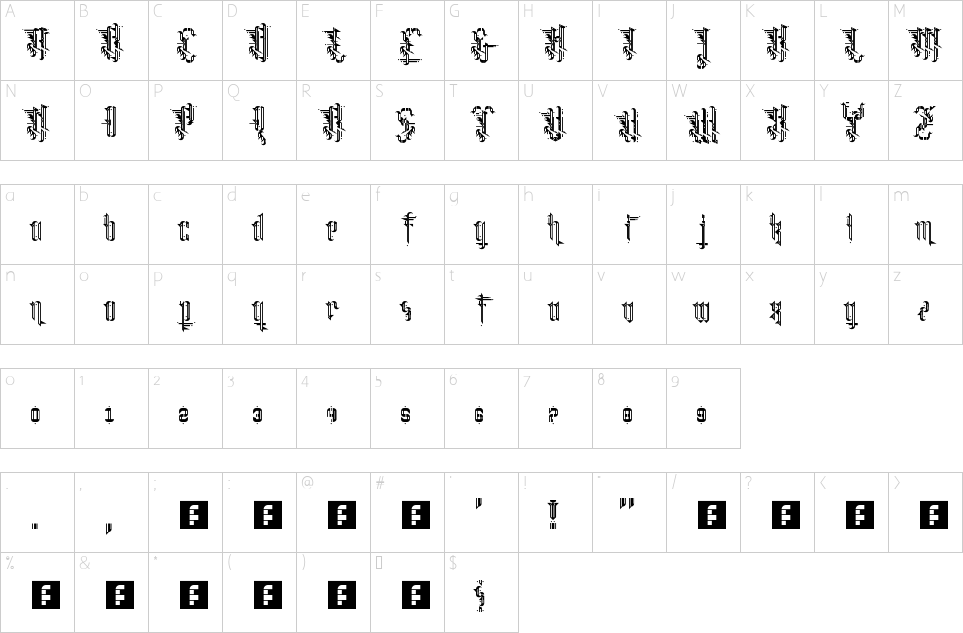
Aqui está uma descrição em português para a página de download da fonte ‘Grimeplex Font – 1001 Free Fonts’, mantendo a essência do texto original e as regras fornecidas: Descubra o poder da Grimeplex, uma fonte gratuita que oferece uma abordagem única para tornar seus projetos ainda mais distintivos. Desenvolvida por Chequered Ink, esta font se destaca não apenas pela sua versatilidade e legibilidade, mas também pelo design moderno e elegante. Grimeplex é a escolha perfeita para designers que desejam incorporar uma personalidade única em seus projetos digitais. Com uma ampla gama de opções estilísticas, Grimeplex permite transformar textos simples em obras de arte vibrantes e únicas. Com sua interface limpa e intuitiva, a Grimeplex está disponível tanto para sistemas operacionais Windows quanto Mac, tornando-a acessível para todos os usuários. Se você busca uma fonte que possa expressar seus ideais criativos com estilo e modernidade, não hesite em experimentar a Grimeplex. Seu design original foi desenvolvido por Chequered Ink, o designer responsável pela criação de uma série de fontes inovadoras e acessíveis. Com sua facilidade de uso e qualidade de impressão avançada, esta font é um verdadeiro trunfo para qualquer projeto de gráficos digitais. Descarregue a Grimeplex agora e explore as possibilidades criativas que ela pode abrir em seus projetos!